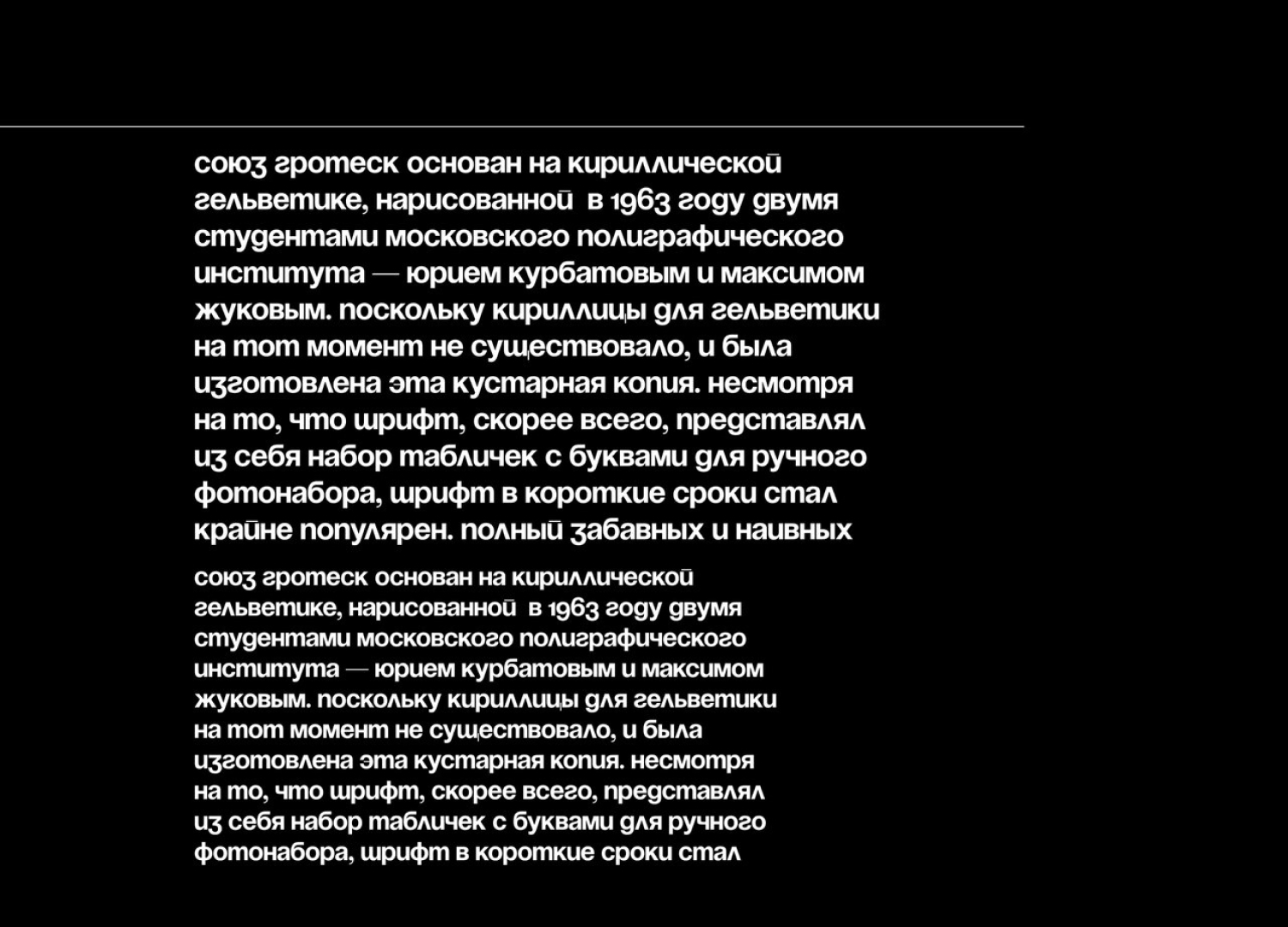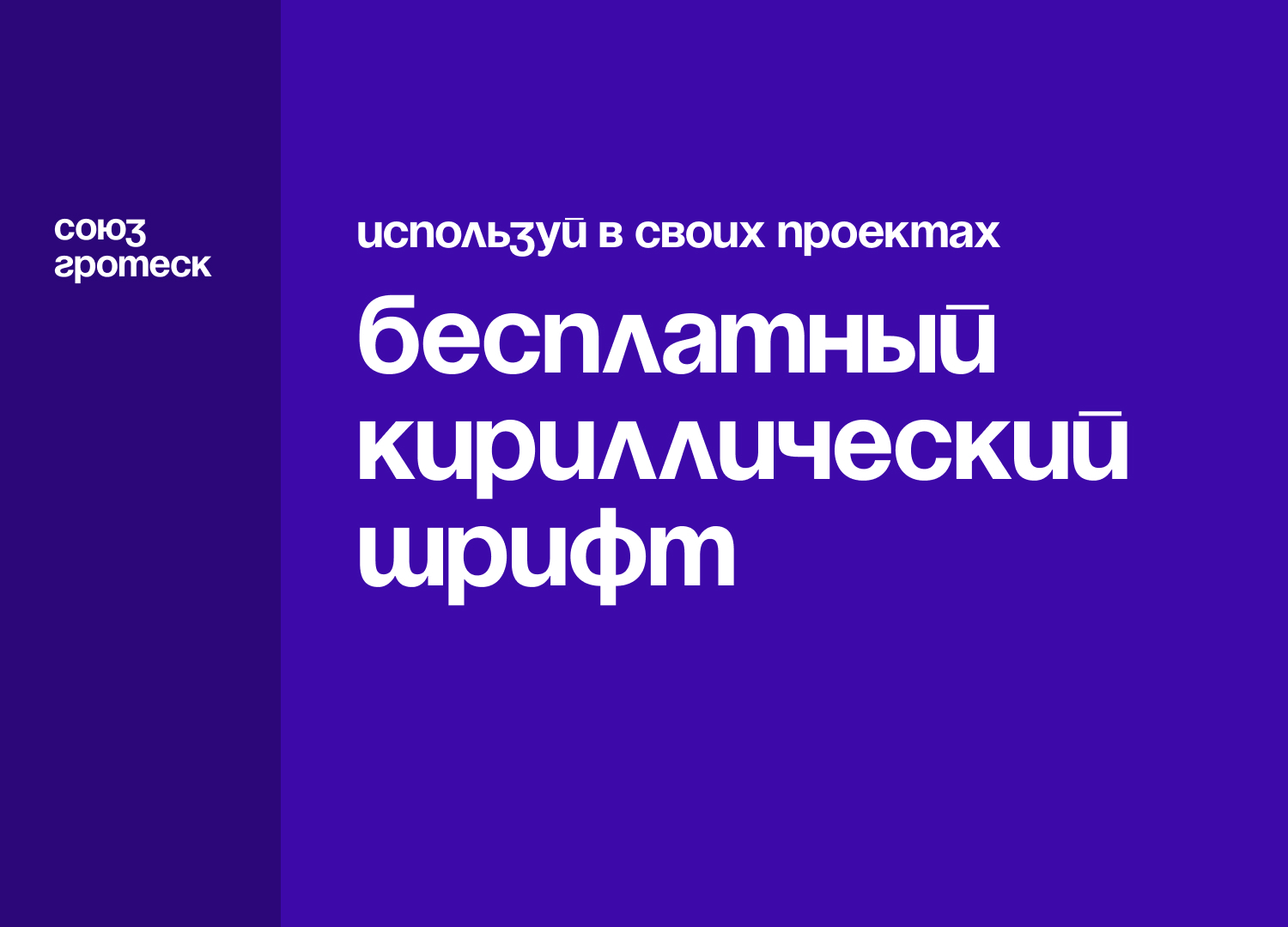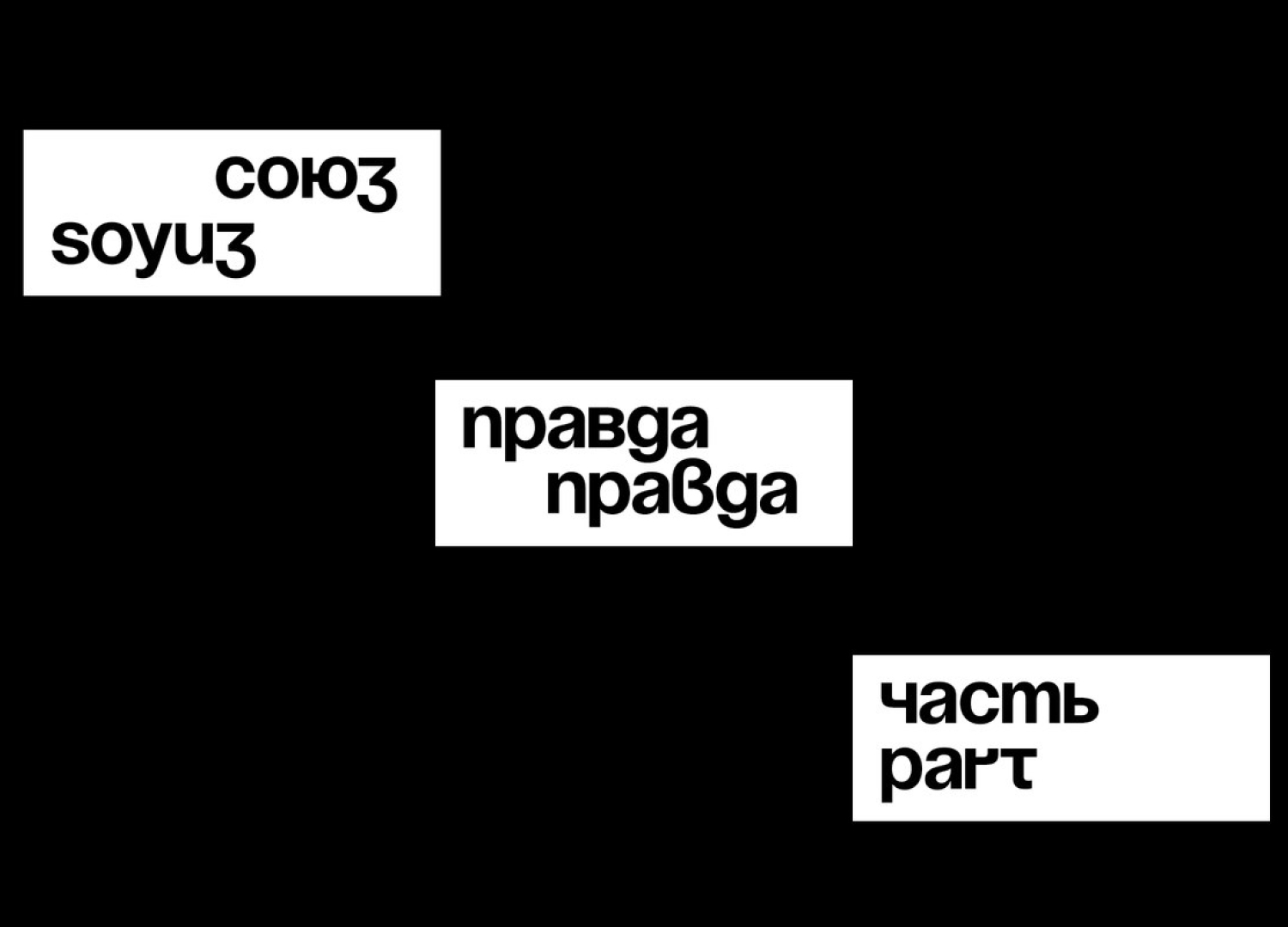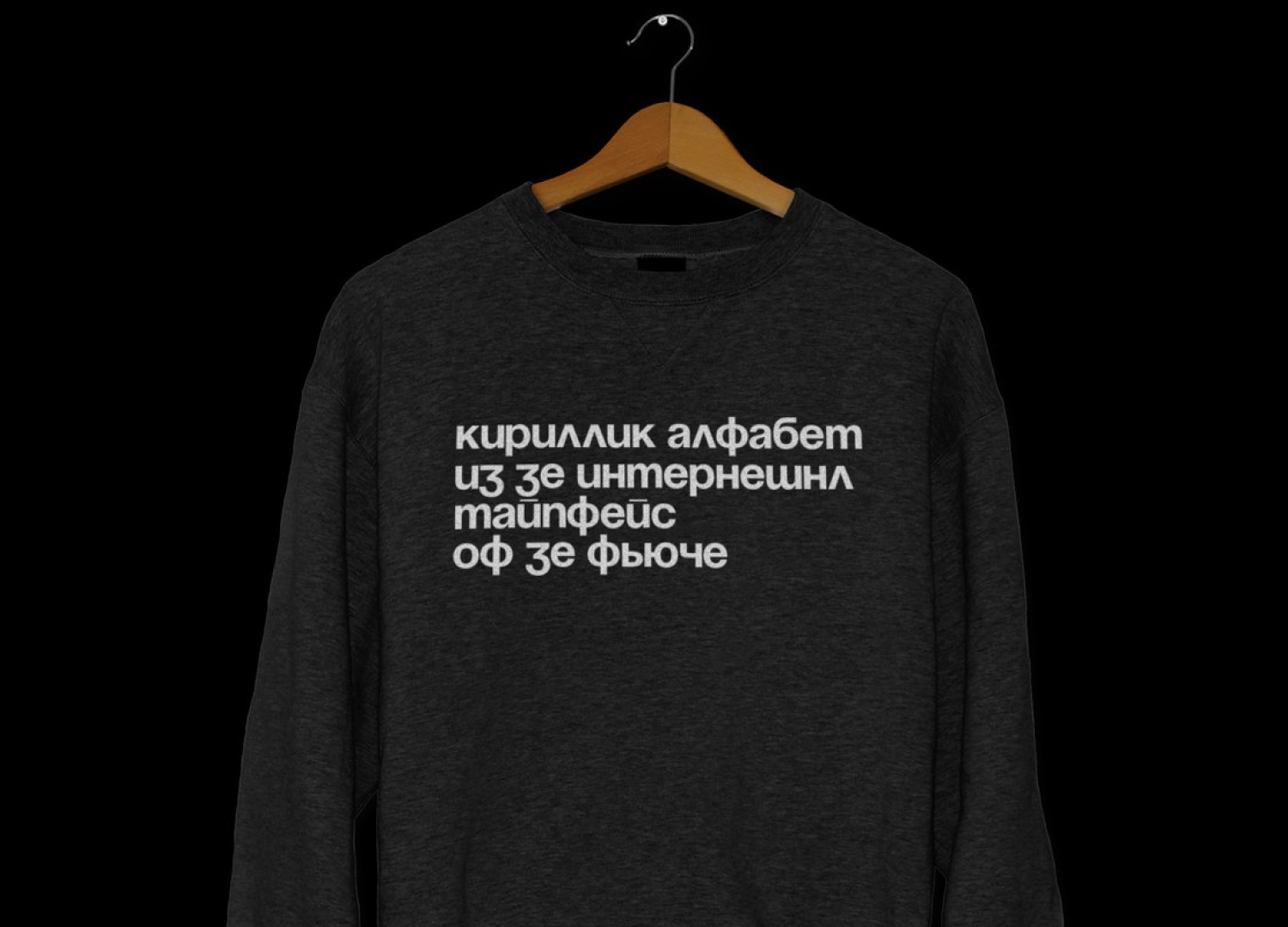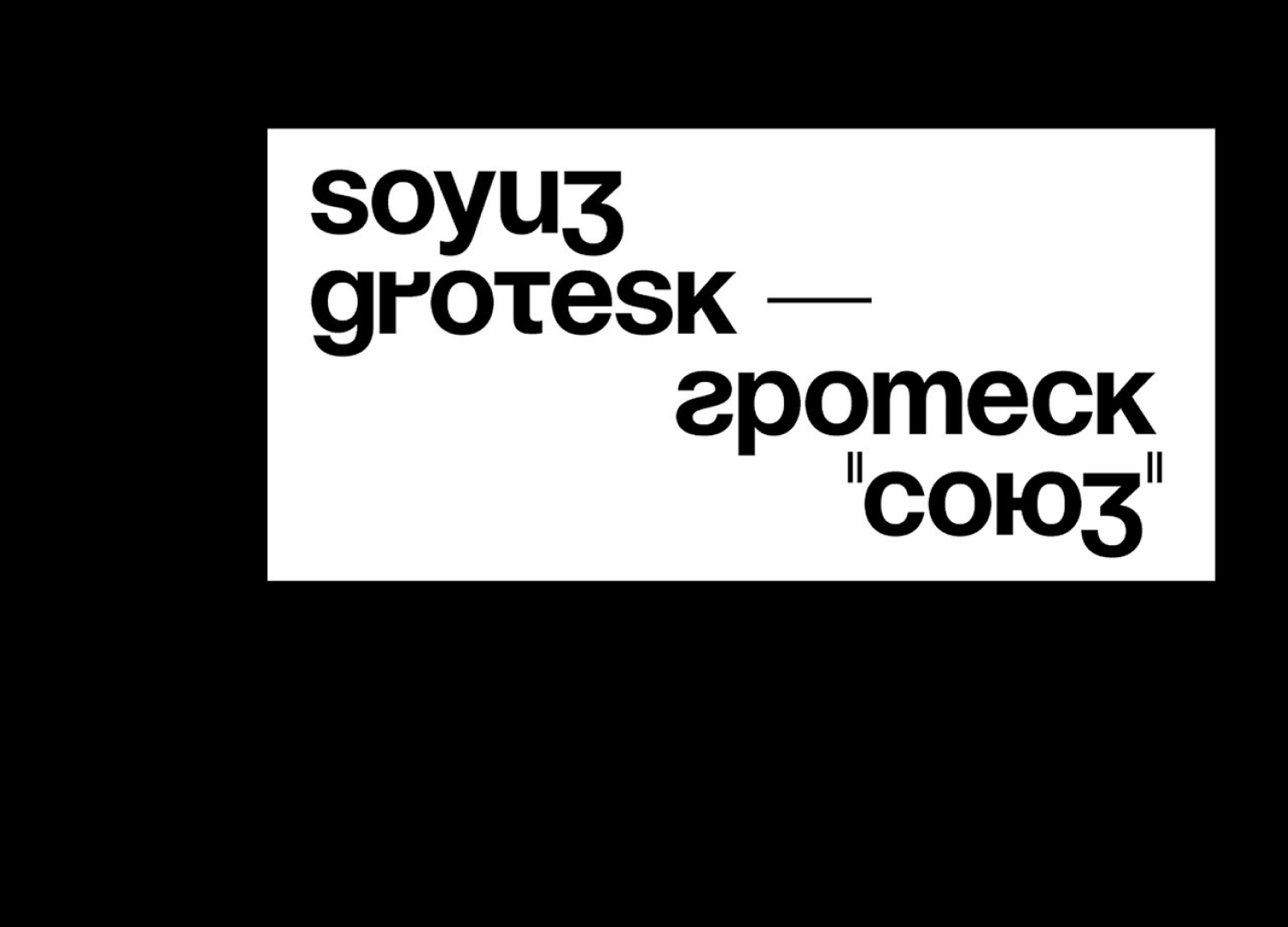
Бесплатный шрифт soyuz
Союз. И даже не мультфильм. Мне определенно нравится этот шрифт. Единственная странность – у него нет заглавных букв. В остальном отличная кириллица. Автор: temporarystate